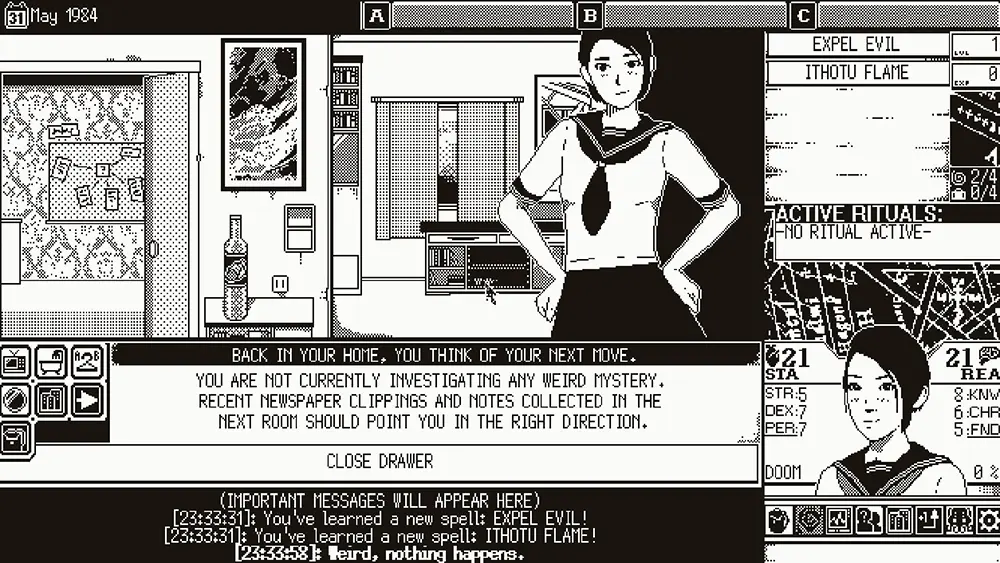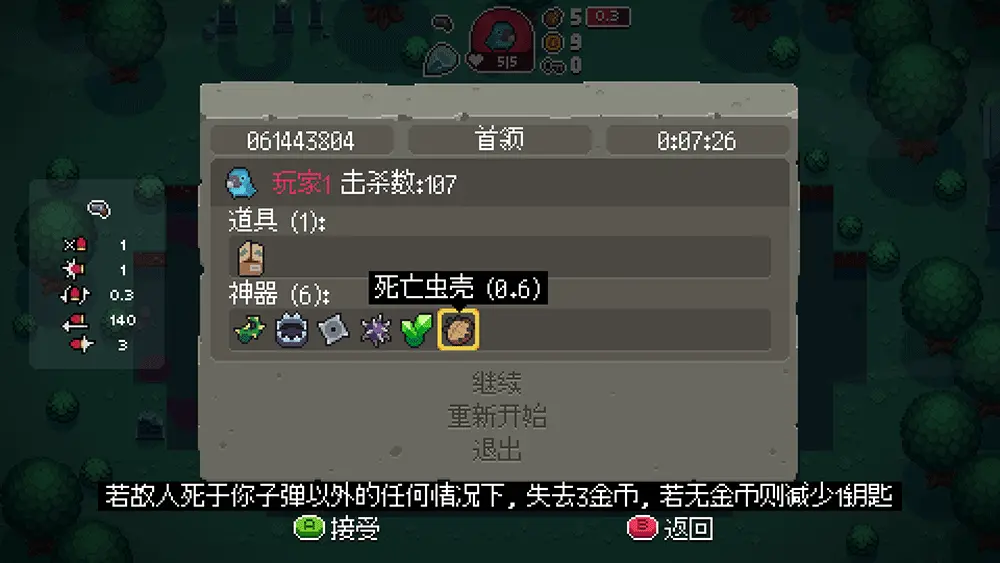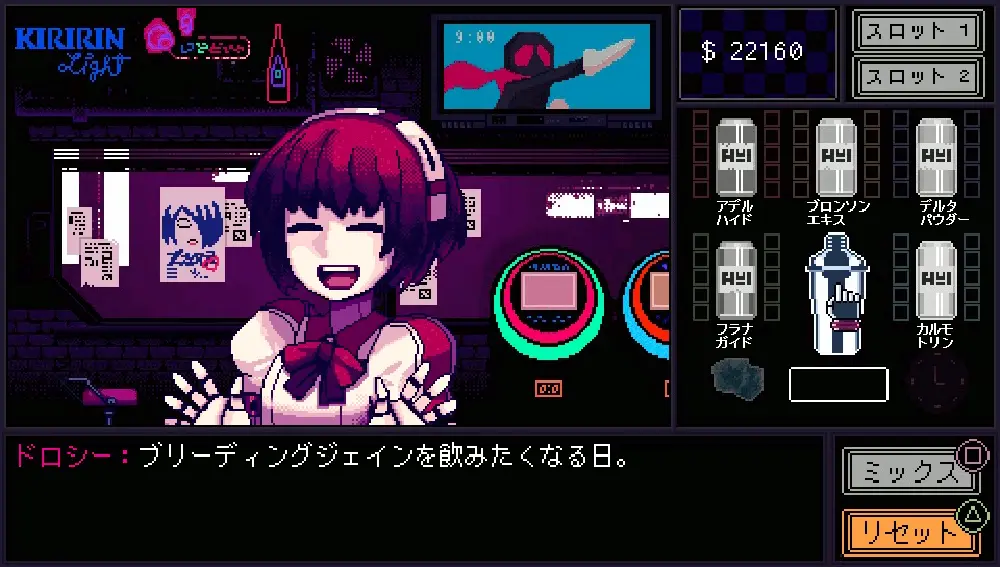
感謝您對Silver的興趣,Silver是遊戲和遊戲愛好者的首選多語言像素字體。Silver在字體中內置了TRC和Lotcheck兼容的遊戲板按鈕,以及完整的鍵盤和鼠標提示!不再在文本字段上疊加圖像!
這是一個正在進行的項目,將不斷更新新的Unicode字形。目標是成為像素遊戲和應用程序的實際字體。
免費的像素字體,適用於拉丁語、中文、韓語、日語、切羅基語、北歐文字、西里爾文和其他字符集。
Thank you for your interest in Silver, the premiere multi-language pixel font for games and game-likers. Silver has TRC and Lotcheck compliant gamepad buttons built right into the font, alongside a full keyboard and mouse prompts! No more overlaying images onto your text fields!
This is an on-going project and will be continuously updated with new Unicode Glyphs. The goal is to be the defacto font for pixel games and applications.
A free* pixel font for Latin, Chinese, Korean, Japanese, Cherokee, Runic, Cyrillic, and other character sets.